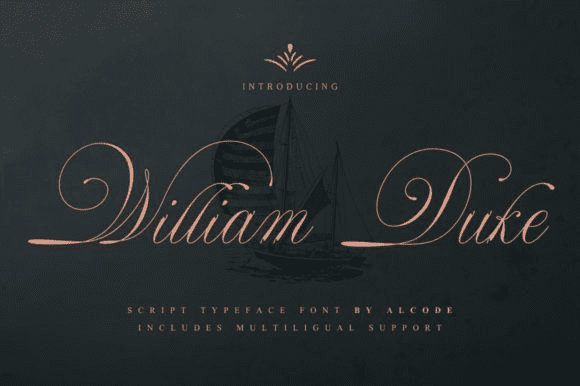
Название: William Duke Font
William Duke - это роскошный и восхитительный сценарий с великолепными мотивами.
Этот классический каллиграфический шрифт выделит любой дизайн-проект.
Название: William Duke Font
William Duke - это роскошный и восхитительный сценарий с великолепными мотивами.
Этот классический каллиграфический шрифт выделит любой дизайн-проект.